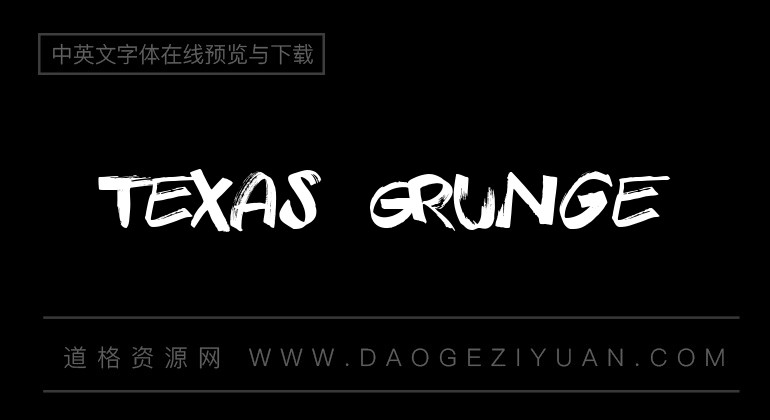
Texas Grunge 是一款极具特色的字体,它具有活泼、复古、粗犷的风格,让人一眼就能感受到它独特的魅力。它的字体构成主要由粗体、斜体和普通字体组成,这些字体都具有活泼的外观,比如粗体的字体具有拉伸的形状,斜体的字体具有倾斜的形状,而普通字体则具有平行的形状。它也具有极具特色的符号,比如可以在字体中使用拉伸的形状,以及可以在文字中使用倾斜的形状。Texas Grunge 字体可以用于制作海报、标志、海报、T恤等,它可以带来活泼、复古、粗犷的风格,让你的作品充满活力。内容介绍
Texas Grunge是一款非常不错的手写艺术字体,具有很好的视觉感,适合于文化类的宣传设计、商业类品牌的广告和产品包装设计以及个性化文字排版等较多场景。